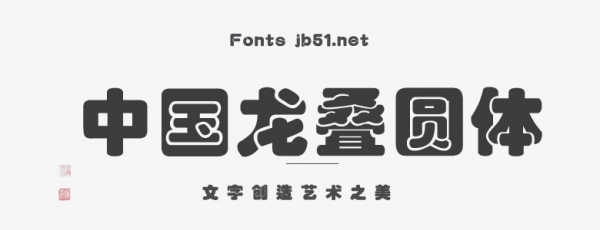
中國(guó)龍疊圓體字體是一款中國(guó)風(fēng)圓形字體軟件,字體工整好看,給人一種整體舒服的感覺(jué),沒(méi)有突出的尖角,非常圓滑,適合應(yīng)用于藝術(shù)設(shè)計(jì)、平面宣傳設(shè)計(jì)、網(wǎng)頁(yè)設(shè)計(jì),書(shū)法字帖等領(lǐng)域。